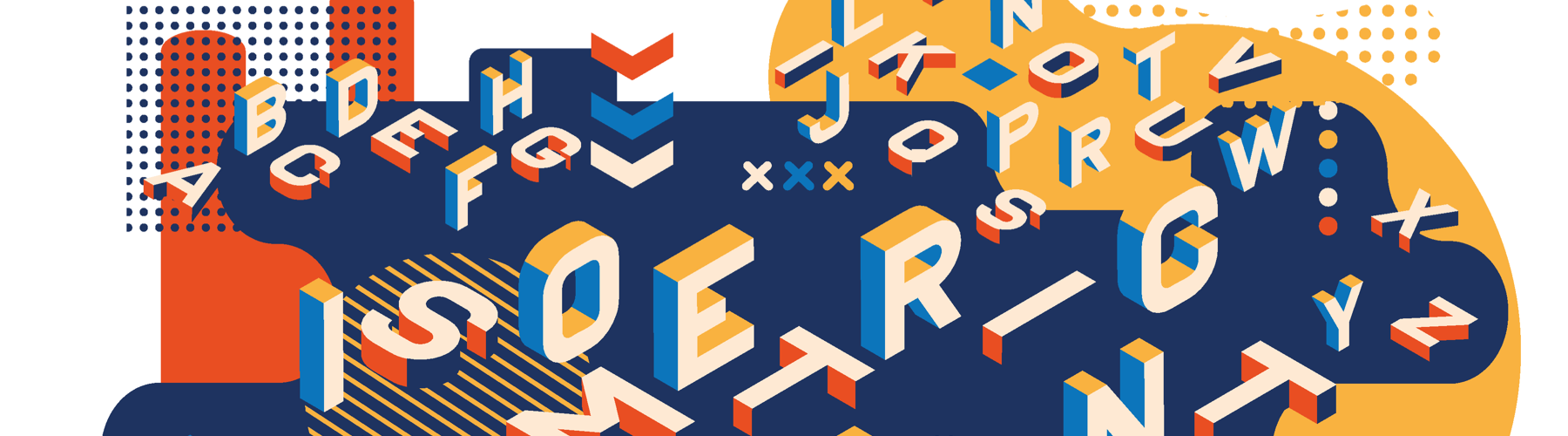
Stai progettando un poster, un volantino o un volantino? Siamo sicuri che hai già pensato alla maggior parte degli elementi che dovete considerare. Come il messaggio che vuoi trasmettere, i colori che userai, dove metterai il tuo logo e così via. Tutti questi aspetti sono molto importanti per un risultato finale efficace. Ma c'è un aspetto che viene spesso trascurato gravemente: la tipografia.
Quando parli, qualsiasi cosa, dalla tua espressione ai tuoi gesti e alla tua postura, gioca un ruolo importante nel messaggio che alla fine passa attraverso di te. Ma quando si tratta di scrivere, ci sono solo le parole e il significato letterale di quelle parole, giusto? Beh, non proprio. Quando si tratta di testo scritto c'è un aspetto che in realtà gioca lo stesso ruolo che il tuo gesto avrebbe per il tuo discorso: la tipografia. Diversi tipi di tipografia hanno la capacità di aggiungere un'emozione diversa al testo.
Sono state fatte molte ricerche per spiegare questo fenomeno. Quando guardiamo il testo, i nostri occhi seguono le righe. Questo rende la lettura un'esperienza fisica reale. Lo si può paragonare al modo in cui si reagisce al linguaggio del corpo delle persone. In un'indagine condotta da Poffenberger e Barrows nel 1933, alle persone è stato chiesto di abbinare le emozioni a diversi tipi di forme. Le linee verso il basso erano considerate "dolorose", mentre le linee verso l'alto davano ai partecipanti un senso di gioia.
Tutte le diverse emozioni a cui puoi pensare, che tu ci creda o no, possono essere espresse con la tipografia. Un paio di psicologi una volta hanno lasciato che più di cento studenti di New York leggessero un articolo satirico del New York Times. Una parte del gruppo ha ricevuto l'articolo Arial e l'altra parte ne ha ricevuto uno sul Times New Roman. In seguito, si è concluso che Times New Roman era il migliore font per un articolo satirico perché sembrava più arrabbiato e divertente.
Tutte queste informazioni possono essere molto preziose sia per il marketing che per i grafici. Quando hai stabilito l'obiettivo della tua campagna di marketing o del design e sai esattamente come vuoi che il consumatore si senta, puoi trovare la tipografia giusta per far sì che ciò accada.